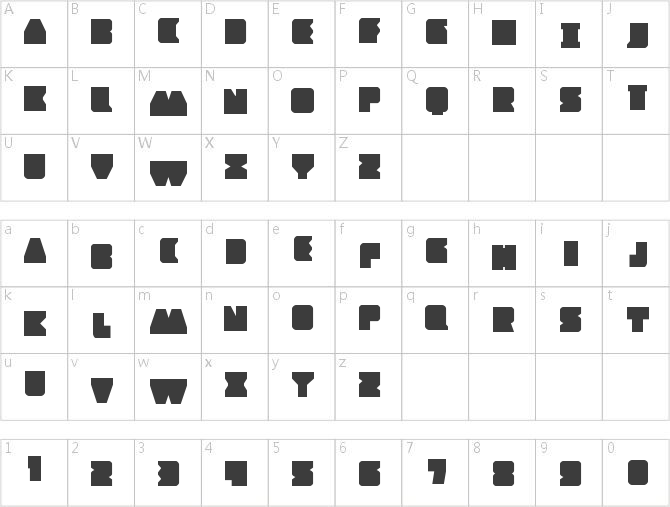
字體名稱: contour
contourofduty
contourofduty字體字庫(kù)是一款讓人賞心悅目、百看不厭的英文字體,適合各類廣告和產(chǎn)品包裝設(shè)計(jì)應(yīng)用,字體大小0.02MB,格式為ttf字體,上傳用戶是快霸中國(guó),作者/版權(quán)方為未知